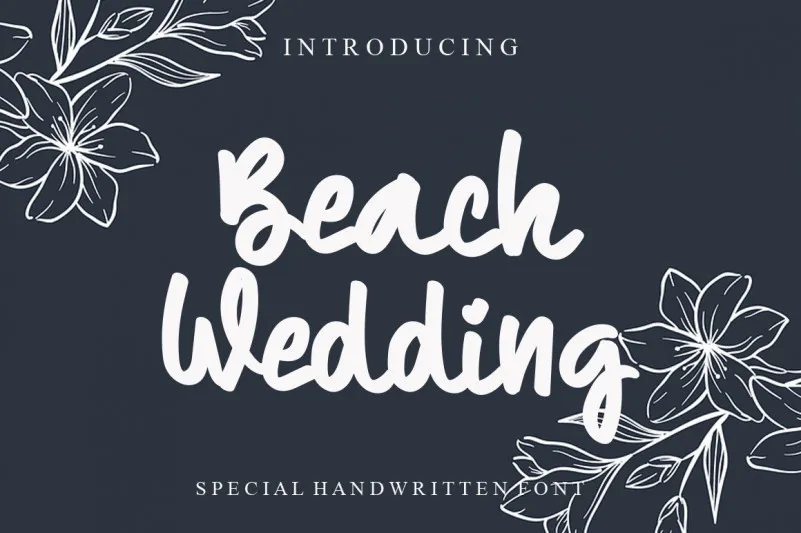
Beach Wedding Font – Download Grátis
A fonte “Beach Wedding Font” criada pelo designer levincreative é uma delicada escolha para qualquer projeto que exige estilo e elegância. Ela se destaca pela sua escrita manuscrita, parecida com a pintura, com linhas suaves e perfeita para estilos de marca fashion ou designs editoriais. Se você está buscando uma fonte que possa dar um toque único aos seus trabalhos, essa é uma ótima opção. “Beach Wedding Font” foi projetada para ser usada com confiança em suas criações e você certamente adorará os resultados. Esta font hand-writtendirigida para categorias de design como moda ou editorial, tornando-a perfeita para qualquer projeto que seja elegante e único.